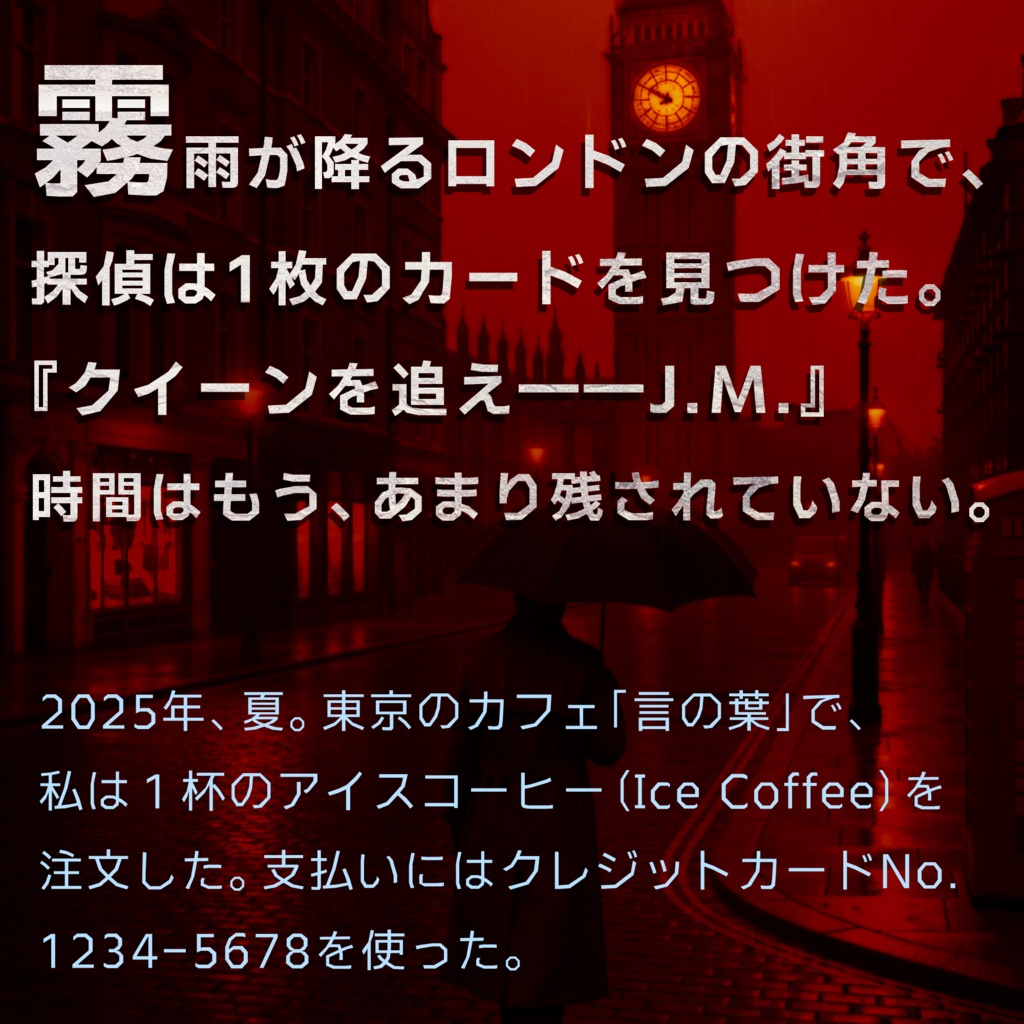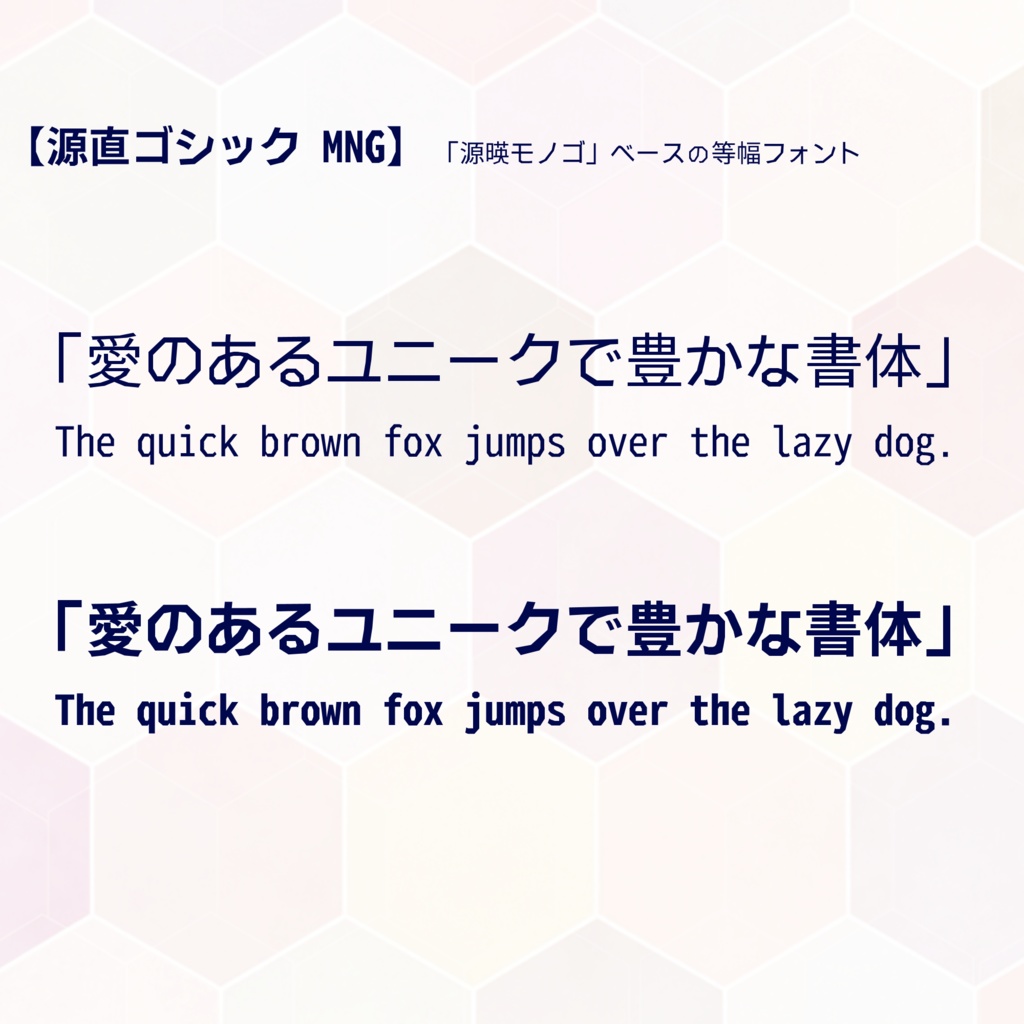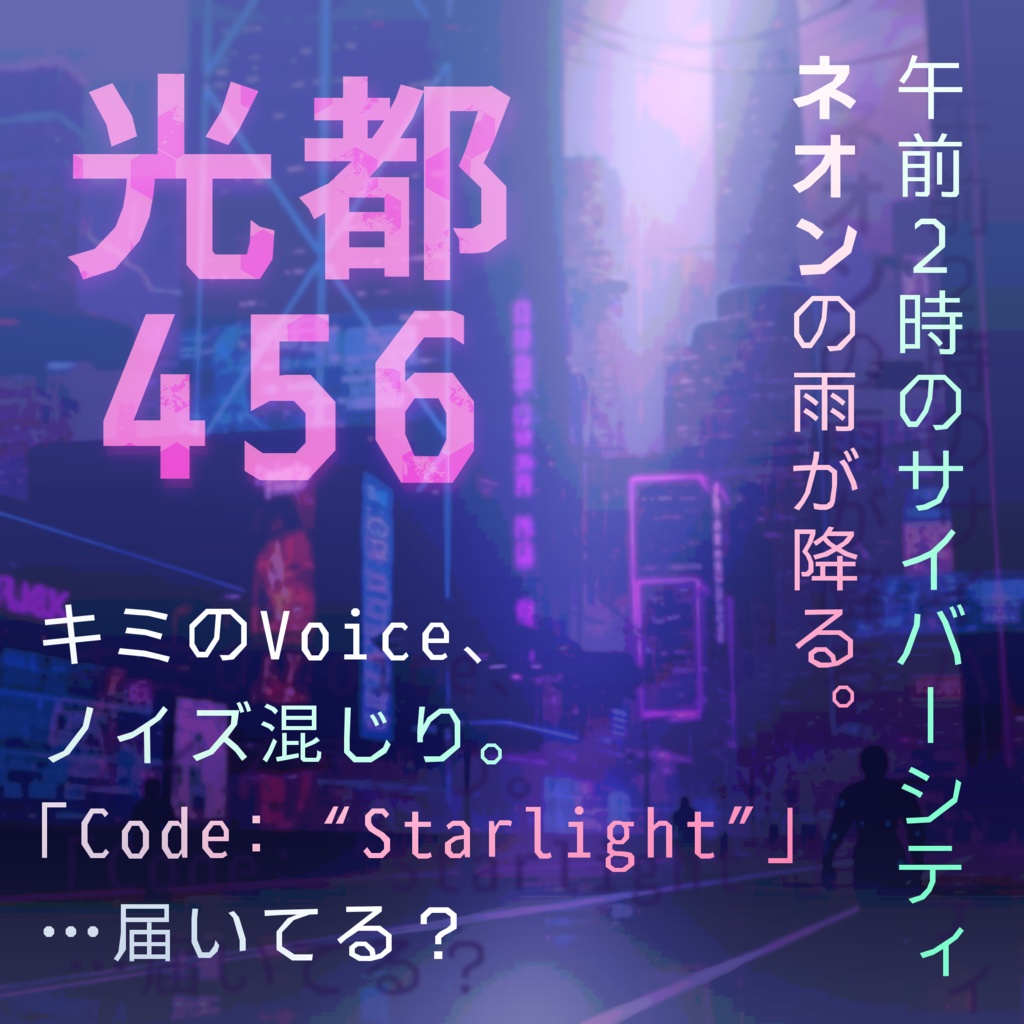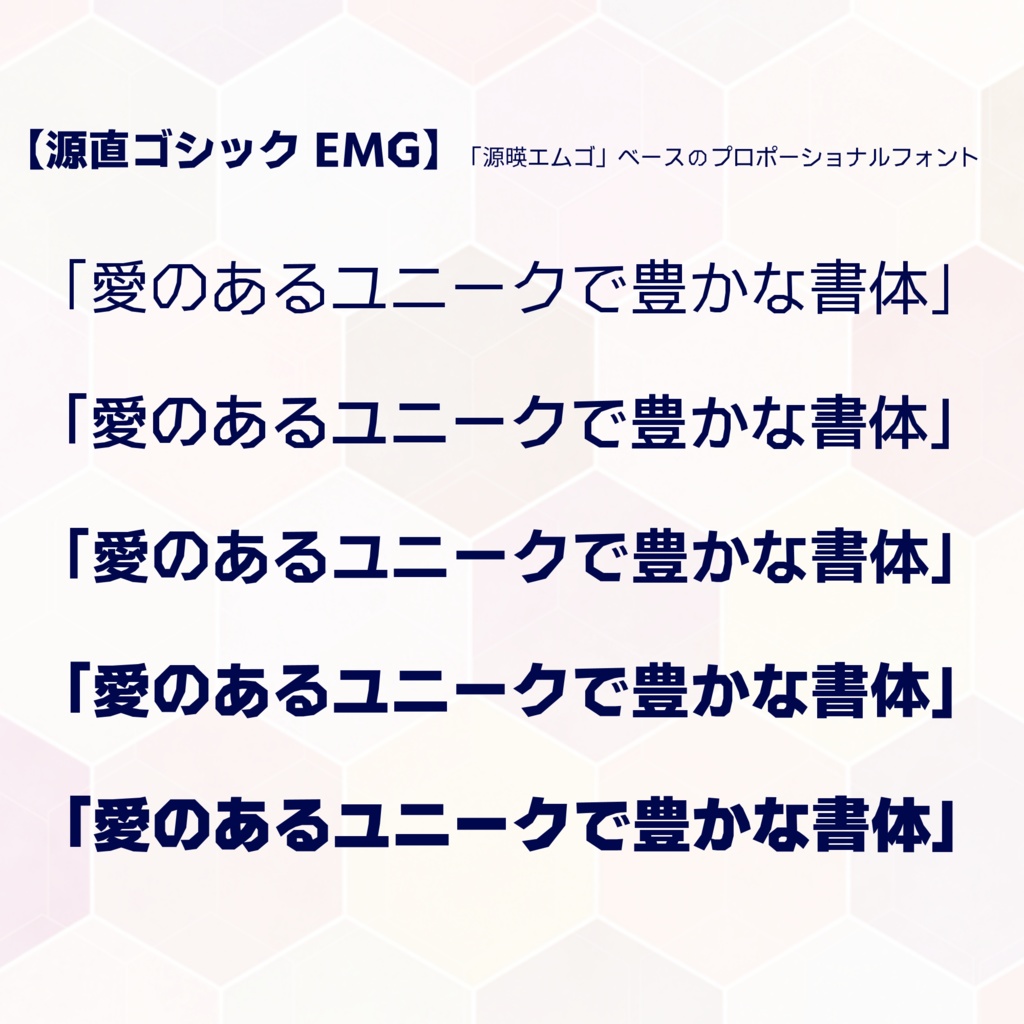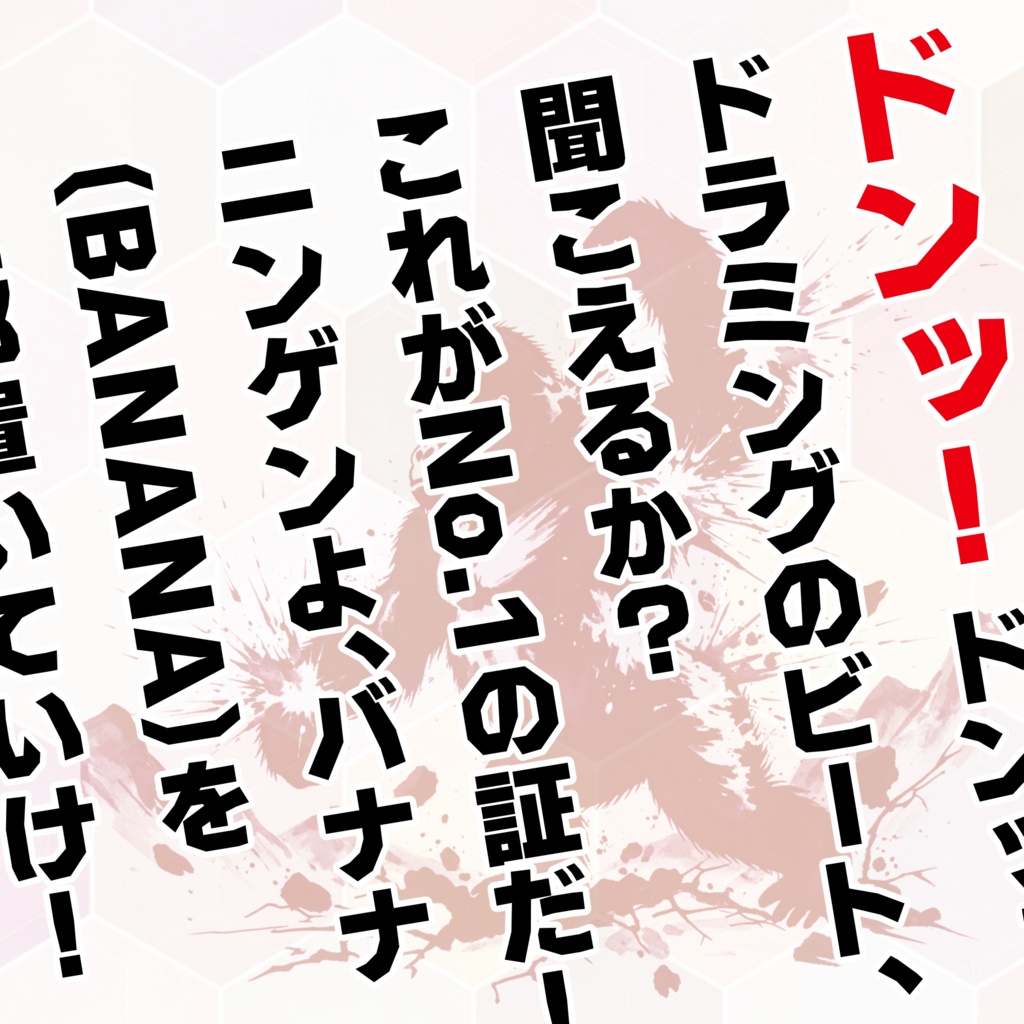
カクカク書体『源直ゴシック』【フリーフォント】
『源直ゴシック』(GenChoku Gothic) 繊細なメッセージから、力強い表現まで。 すべてが直線のみで構成された、ユニークなゴシック体フォントです。
■ 源直ゴシック EMG(全5ウェイト) 「源暎エムゴ」 ベースのフォントです。 ■ 源直ゴシック MNG (全2ウェイト) 「源暎モノゴ」ベースの等幅フォントです。 ※いずれのフォントも縦書きに対応しています。
本フォントは、オープンソースフォント 『源暎エムゴv2』(GenEiMGothic2) https://okoneya.jp/font/genei-m-gothic.html 『源暎モノゴ』(GenEiMonoGothic) https://okoneya.jp/font/genei-mono-go.html を元に制作しました。 素晴らしいフォントを公開してくださった制作者様に心より感謝申し上げます。 ■ ご利用にあたって ・本フォントは、元フォントを一括で直線化加工した後、英数字・ひらがな・カタカナを微調整したものです。 ・漢字については調整をほとんど行っていないため、フォントのバリエーションによっては一部の文字で字形が若干崩れて見える場合があります。 ・気になる部分には、ベースとなった「源暎エムゴ」「源暎モノゴ」を混ぜて使う(混植する)と、より自然な表現が可能です。